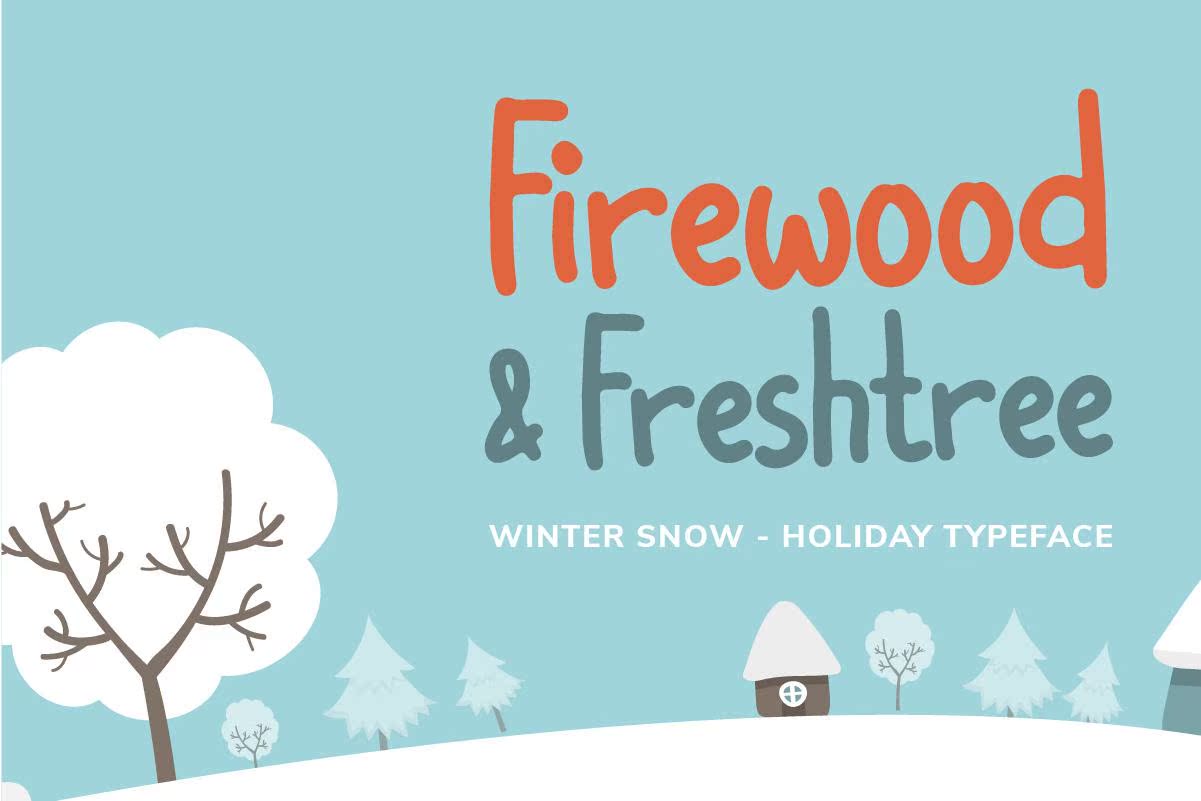
简介IntersNow字体。它由Wyare Creative Type设计。Wintersnown是Wyear的元素。受到度假情绪的启发,为我们的未来创造了精彩的作品。非常适合标题、短文本、明信片、日历、杂志、书籍和徽标。尽情享受吧!🙂简介IntersNow字体。它由Wyare Creative Type设计。Wintersnown是Wyear的元素。受到度假情绪的启发,为我们的未来创造了精彩的作品。非常适合标题、短文本、明信片、日历、杂志、书籍和徽标。尽情享受吧!🙂